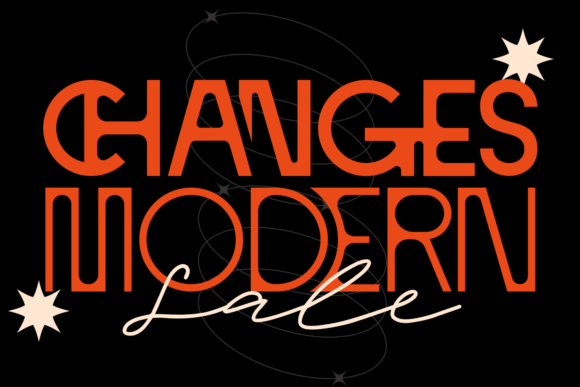
Changes Modern
Changes Modern – Revue détaillée du nouveau sans‑serif polyvalent
Si vous cherchez une police qui allie force et ludisme, Changes Modern répond parfaitement à ces exigences. Cette police OT offre un contraste inversé qui lui confère un aspect moderne et épuré, tout en restant très lisible grâce à la netteté de ses formes.
Points forts de Changes Modern
- Design équilibré : chaque glyphe a été pensé pour garder une harmonie entre le jeu de lignes et la rigueur géométrique, ce qui garantit une lecture fluide même à petite taille.
- Compatibilité OpenType : plus de 100 ligatures, alternatives, chiffres et ponctuations, idéales pour des compositions typographiques riches.
- Support multilingue : la police inclut des caractères pour plusieurs langues, facilitant son utilisation dans des projets internationaux.
- Polyvalence d’usage : parfaite pour le branding, les magazines, les logos, les titres, les affiches, le packaging, les cartes de visite et même les invitations de mariage.
- Aspect intemporel : son style sobre mais audacieux donne à chaque création un look professionnel qui ne se démode pas.
Pourquoi choisir Changes Modern pour vos projets?
En intégrant Changes Modern à votre identité visuelle, vous bénéficiez d’une police qui transmet à la fois confiance et créativité. Sa netteté visuelle attire l’œil sans sacrifier la logique typographique, ce qui assure un équilibre visuel optimal dans chaque composition.
Utilisations concrètes
- Branding : créez des logos mémorables avec des lettres fortes et nettes.
- Magazine & Editorial : des titres percutants qui captent l’attention du lecteur.
- Packaging : un rendu élégant qui met en valeur vos produits en rayon.
- Invitations de mariage : une typographie chic qui ajoute une touche de raffinement.